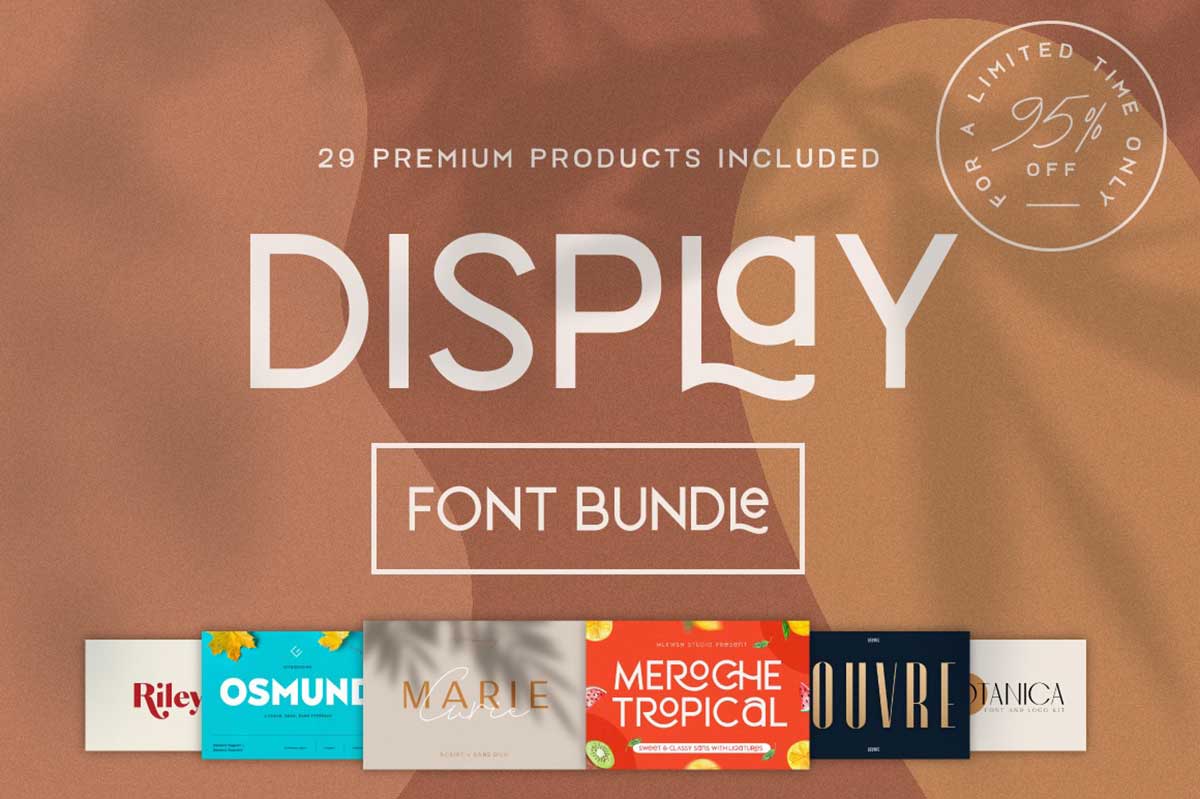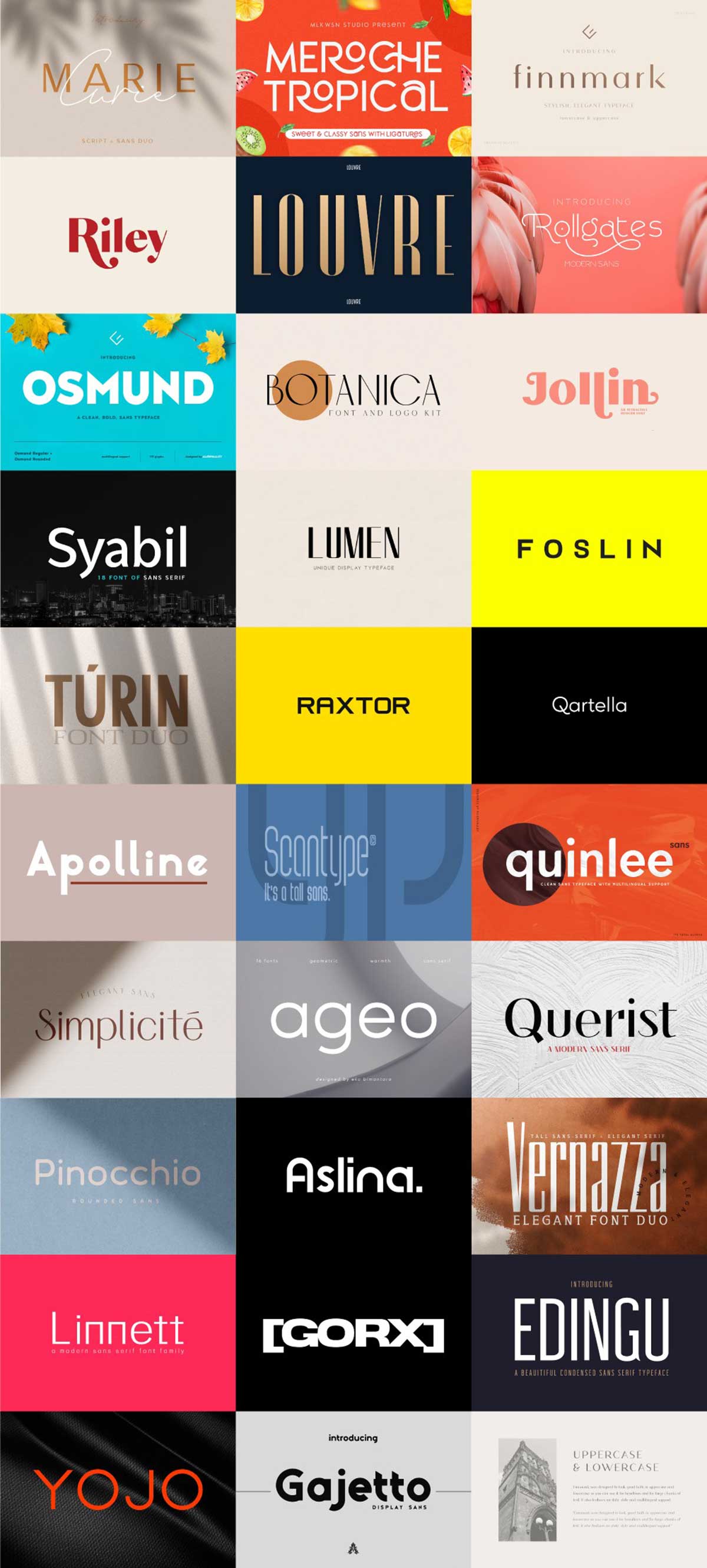
「The Modern Display Font Bundle」の気になる内容
今回のバンドルの中で、私が特に気になるフォントはこちらです。
Querist
「Querist」は、線の強弱がはっきりしたモダンなサンセリフフォント。Pixel Surplusオリジナルフォントで、ただ文字を組むだけでおしゃれな雰囲気になる便利な書体です。
Riley
タイトルや見出しなどに使うと効果的な「Riley」。読みやすさとデザイン性のバランスがちょうどいいフォントです。
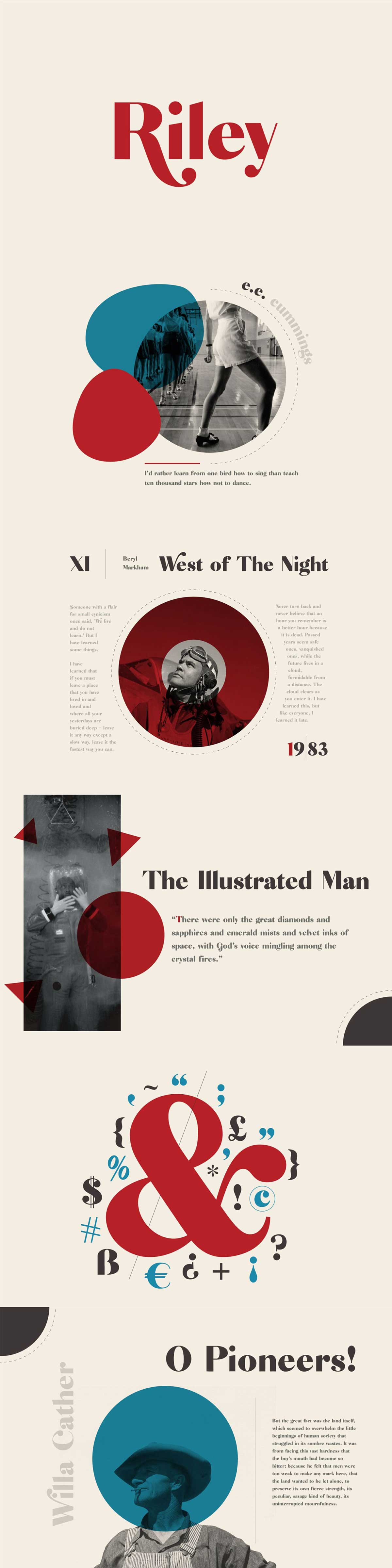
Louvre
大胆に細いウェイトが特徴の「Louvre」。画像のようにグラデーションをかけるだけで高級感が演出できます。
Simplicite
繊細でエレガントな印象の「Simplicite」。連字処理がユニークで、ロゴ作成やブランディングに向いています。
Osmund
通常盤と角が丸いタイプの2書体を収録した「Osmund」。文字を小さくしても読みやすいので、幅広い用途に使えそう。